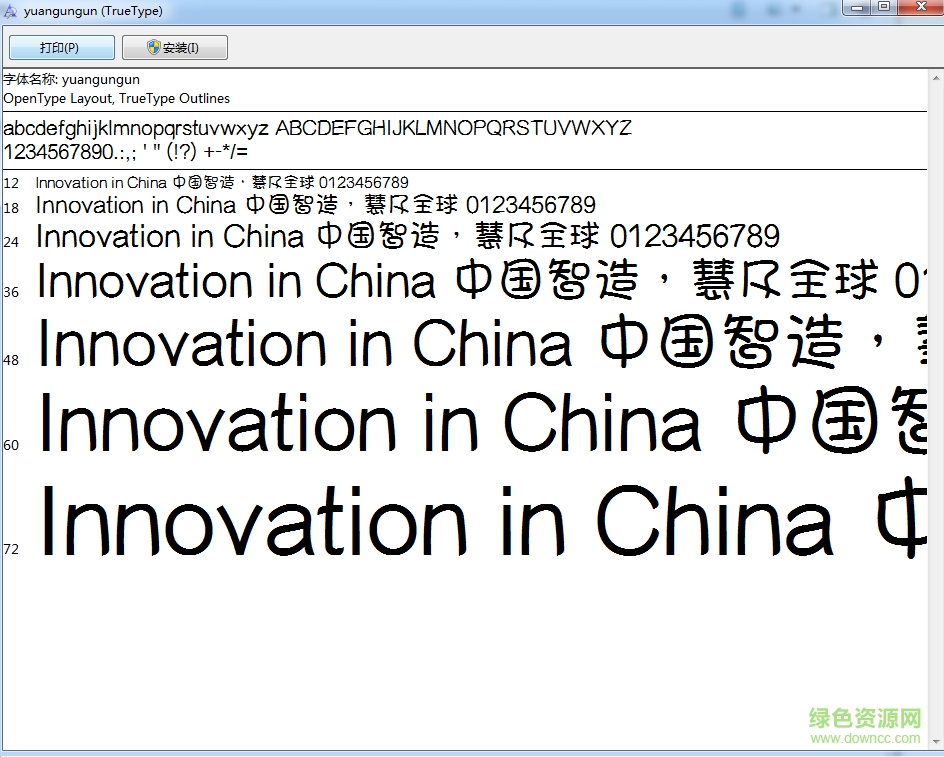
軟件介紹 軟件標簽: 漢堡包字體 字體 漢堡包字體是一款形狀可愛的胖字體,很有輕松活動、搞笑的韻味,讓你的文字設計、廣告創(chuàng)意、印刷排版更顯年輕可愛,綠色資源網為大家免費提供!安裝說明方法一:直接將字體復制到C:\WINDOWS\Fonts方法二:針對win7系統(tǒng),用戶只需選中字體右鍵安裝即可方法三:控制面板/字體/文件/安裝新字體溫馨提示本站所有字體資源僅供個人學習與參考,如需商業(yè)使用請到相關官網授權。 軟件截圖 上一張下一張(1 / 1) 安裝詳細截圖 其他版本下載 標題 大小 更新日期 下載 下載地址 電腦版 漢堡包字體ttf 點擊報錯 軟件無法下載或下載后無法使用,請點擊報錯,謝謝! 關閉報錯反饋 請描述您所遇到的錯誤,我們將盡快予以修正,謝謝! *必填項,請輸入內容 本類最新 dreamweaver字體庫 首爾南山體字體 v1.06 官方版 潮字社風云簡ttf 潮字社凌渡鯤鵬簡體字體 潮字社曾玉波手書簡字體 微博慧心字體 相關文章 Photoshop字體安裝使用方法和技巧 如何解決“無法新增字體”問題 Win 7系統(tǒng)安裝字體方法 網頁字體大小設置方法 怎么改網頁字體大小 在Linux系統(tǒng)中安裝字體的幾種方法 windows7字體顯示問題:打開某些程序的時候顯示的是亂碼 用戶評論 熱門評論 最新評論 發(fā)表評論 查看所有評論(0) 昵稱: 請不要評論無意義或臟話,我們所有評論會有人工審核. 字數: 0/500 (您的評論需要經過審核才能顯示)